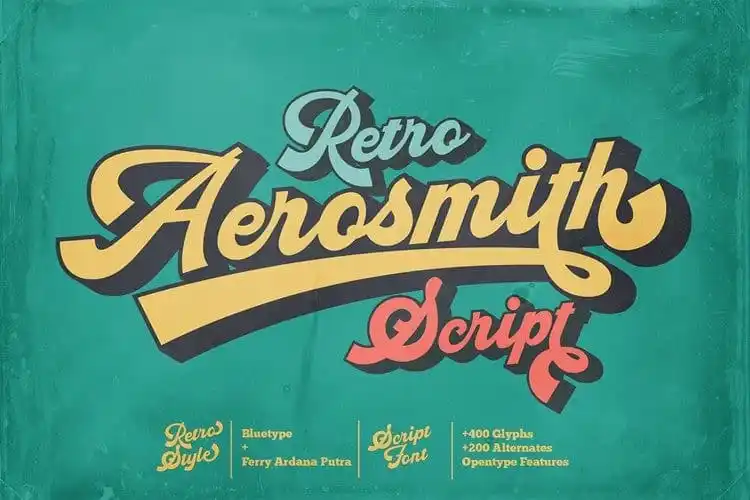
Aerosmith Script Font – Download Grátis
AeroScript é uma fonte círca original, feita para designers que buscam trazer aos seus projetos um toque retro, moderno e vintage semelhante ao da cultura dinâmica de marcas e selos. Inspirada na estética vibrante de tatuagens e logotipos, este tipo de fonte é perfeitamente adequado para designers que desejam incorporar em seus trabalhos um toque nostálgico e criativo. AeroScript vem do design da fonte Bluetype, inspirada na famosa música Aerosmith. Com seu estilo círca, esta fonte é ideal para criações retro, evocando imagens de anos 80 e 90 que muitos associam com a estética rock e pop. Utilizando AeroScript em seus projetos, você terá uma ferramenta poderosa para criar designs retro sem esforço. Seja um designer de identidade visual ou criativo, esta fonte é certamente uma opção a ser considerada.